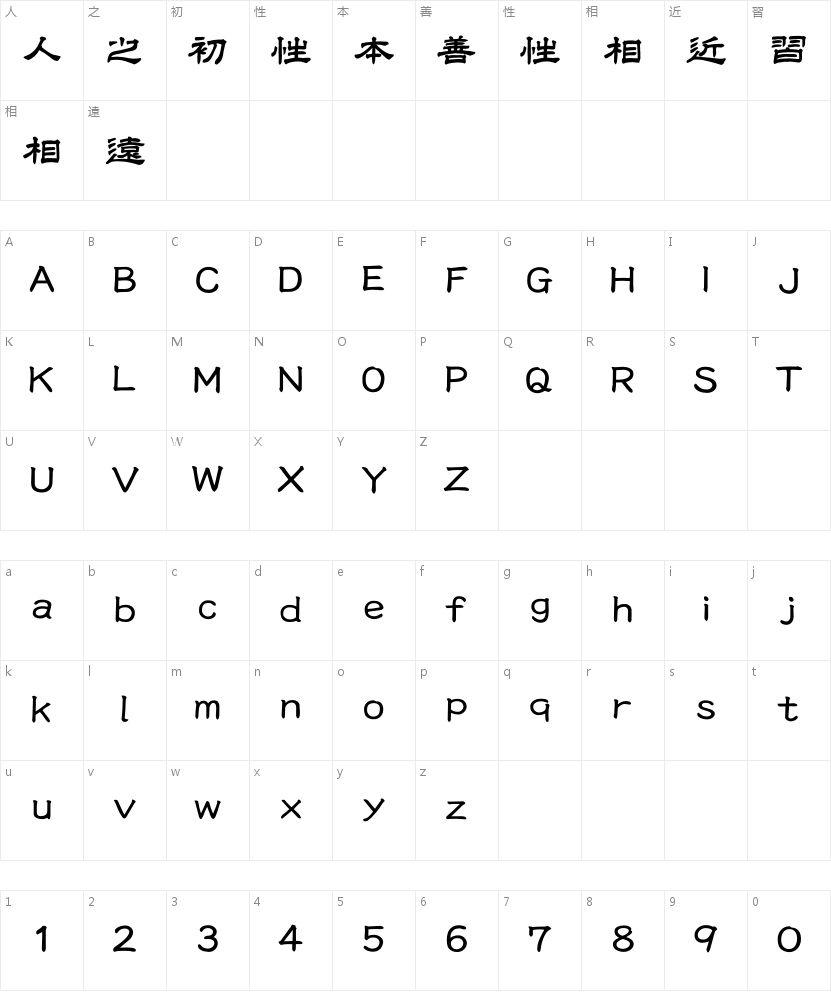
? HOT-白舟太隷書R 字體是一款以漢字繁體字為基礎的中國古典字體,具有傳統的中國風格,深受收藏家和藝術家喜愛。該字體具有清晰的線條,深沉的色彩,細膩的細節,清新的筆觸,以及精緻的構圖,可以用於各種類型的文章,比如古典文學、詩歌、書法、繪畫等。內容介紹
HOT-白舟太隷書R是一款非常不錯的手寫藝術字體,具有很好的視覺感,適合於文化類的宣傳設計、商業類品牌的廣告和產品包裝設計以及個性化文字排版等較多場景。